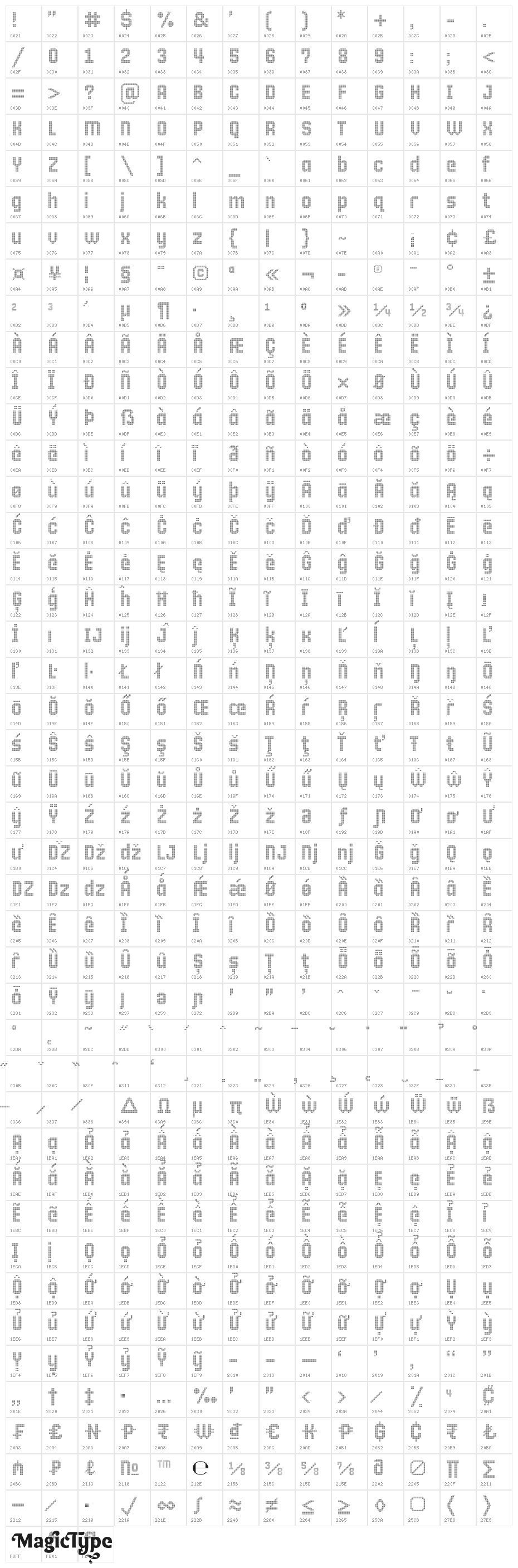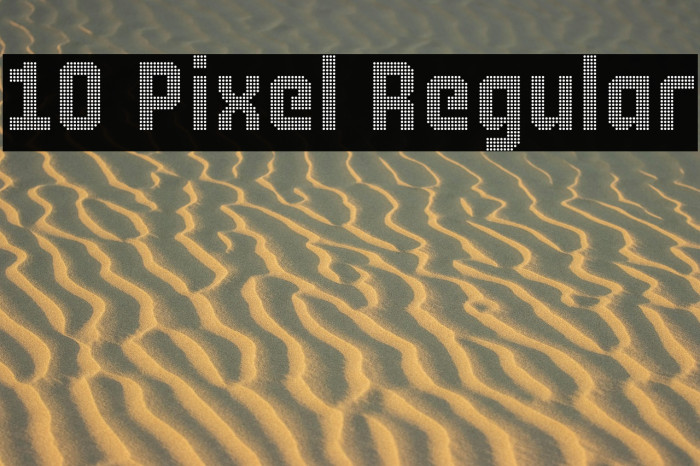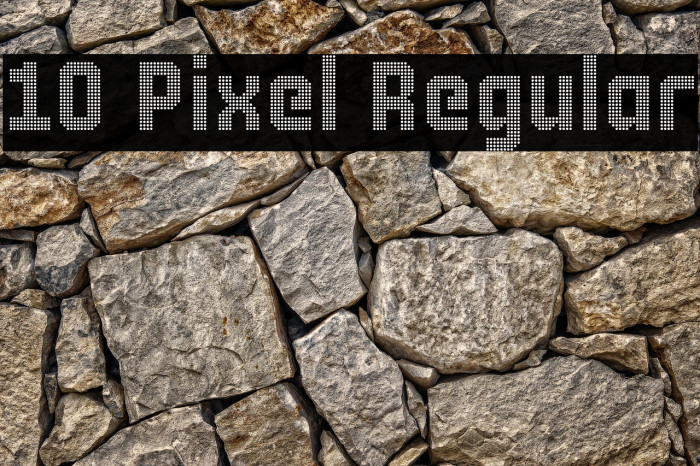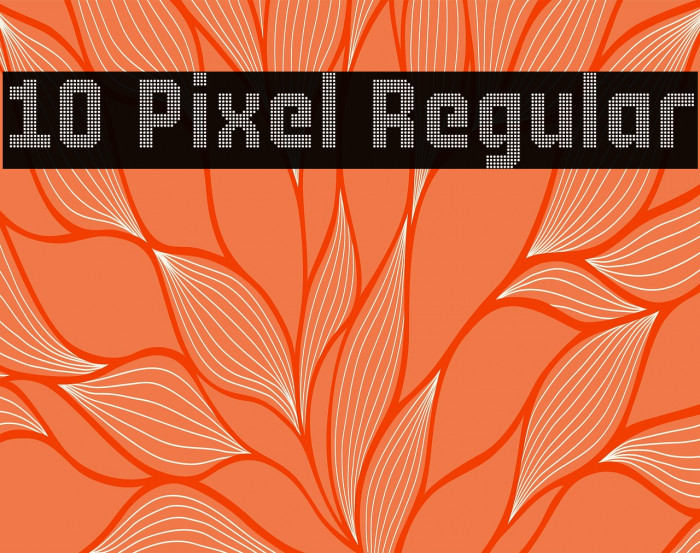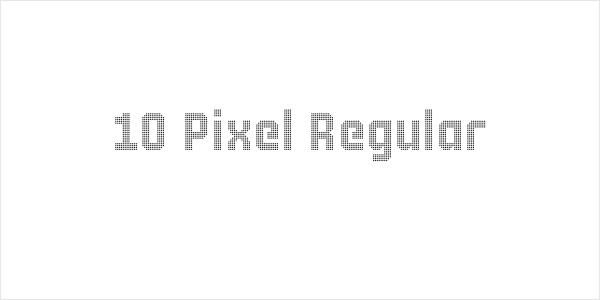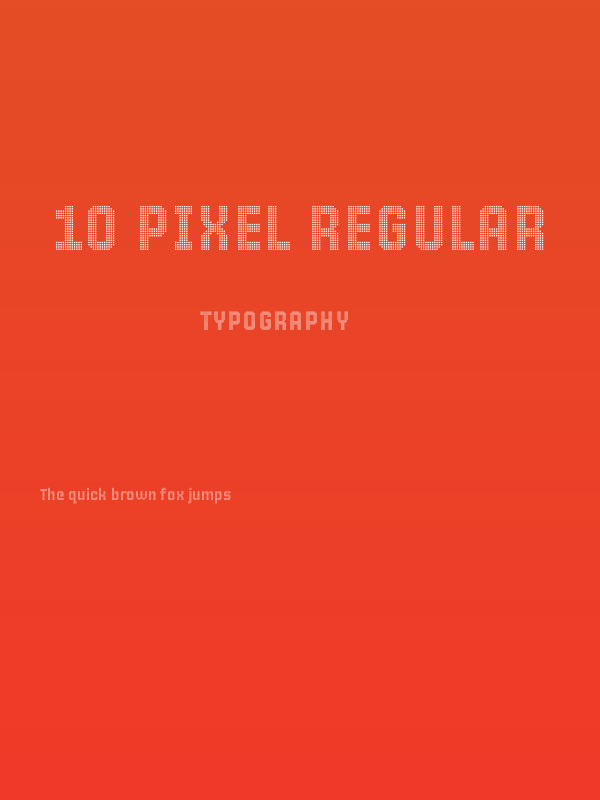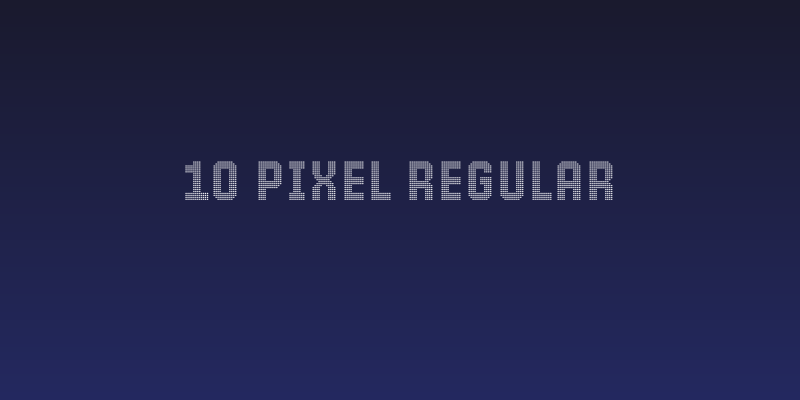
10 Pixel Regular Font
| Anwendungsfall | Logos, Digital displays, Tech interfaces |
| Vorgeschlagene Projekte | Ideal for digital displays, tech-themed designs, retro gaming interfaces, and modern advertising. |